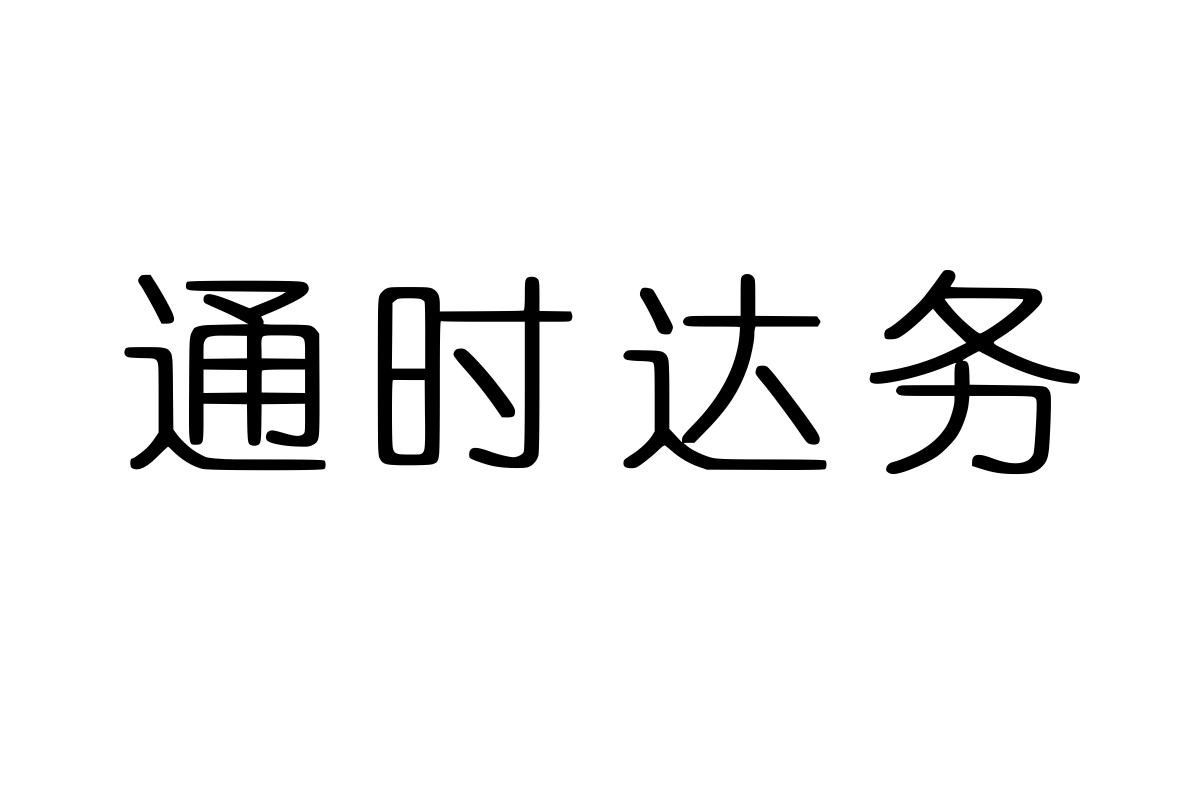
兰米中圆体字体是一款具有独特美感的中文字体,其特点如下:
1. 字形结构:兰米中圆体字体采用了传统的中文字形结构,包括横、竖、撇、捺等基本笔画,以及一些常见的偏旁和部首。这种结构使得字体看起来既有传统韵味,又不失现代感。
2. 笔画粗细:兰米中圆体字体的笔画粗细适中,既不过于纤细,也不过于粗壮。这使得字体在视觉上显得稳重而有力,适合用于标题、正文等多种场合。
3. 字形风格:兰米中圆体字体的字形风格独特,呈现出一种圆润、饱满的特点。这种风格使得字体在阅读时给人一种舒适、亲切的感觉,非常适合用于儿童读物、杂志、报纸等需要传递温馨氛围的场合。
4. 兼容性:兰米中圆体字体具有良好的兼容性,可以很好地融入各种设计元素中。无论是在网页设计、平面设计还是包装设计等领域,都可以发挥出独特的魅力。
总之,兰米中圆体字体是一款具有独特美感和实用性的中文字体,适合用于各种需要传递温馨氛围的设计场景。